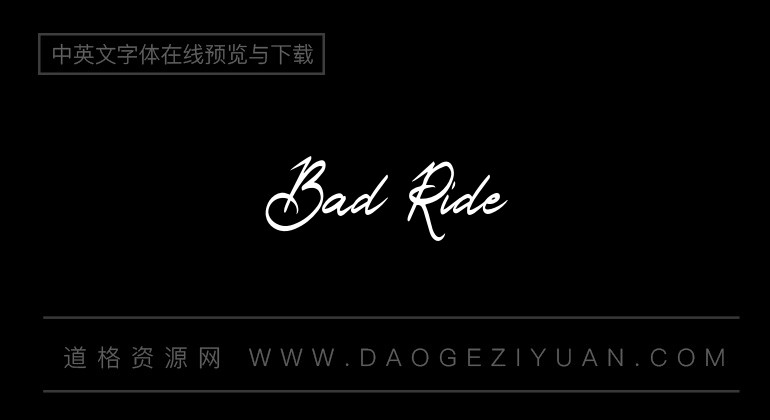
Bad Ride
Bad Ride 是一种充满个性和独特风格的字体,它的特点是笔画粗细不一,有些笔画甚至是不完整的。 这种字体常常被用于设计海报、音乐专辑封面等场合,因为它能够很好地表达出年轻、前卫、叛逆、乱糟糟的感觉。它的字母形状也比较奇特,有时候甚至很难辨认,但正是这种不规则的形状才让 Bad Ride 在视觉上更加引人注目。 Bad Ride 字体可以在多个设计软件中使用,如 Adobe Photoshop、Illustrator、InDesign 等。如果您需要一种有力、有个性、有冲击力的字体来增加您设计作品的视觉效果,Bad Ride 是一个不错的选择。
Bad Ride是一款非常不错的手写艺术字体,具有很好的视觉感,适合于文化类的宣传设计、商业类品牌的广告和产品包装设计以及个性化文字排版等较多场景。